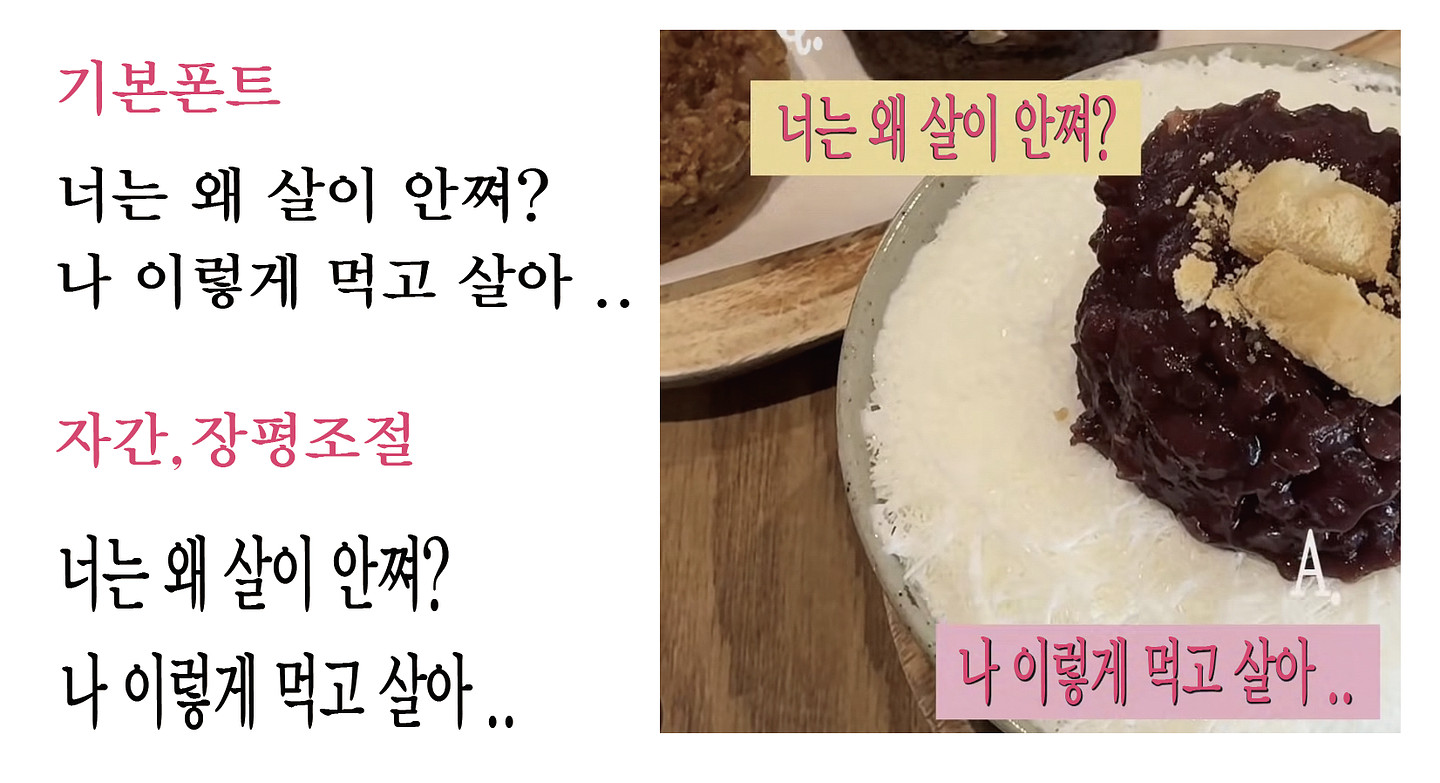
Keris(한국교육학술정보원)
학교안심 바탕체입니다! 기본폰트에서 자간+장평 조절했네요! AI올컷님이 만드신 신야르폰트 사용하시면 자간+장평이 조절된 폰트라서 따로 조정하실 필요없이 사용가능합니다! https://blog.naver.com/aiollcut/224378747525